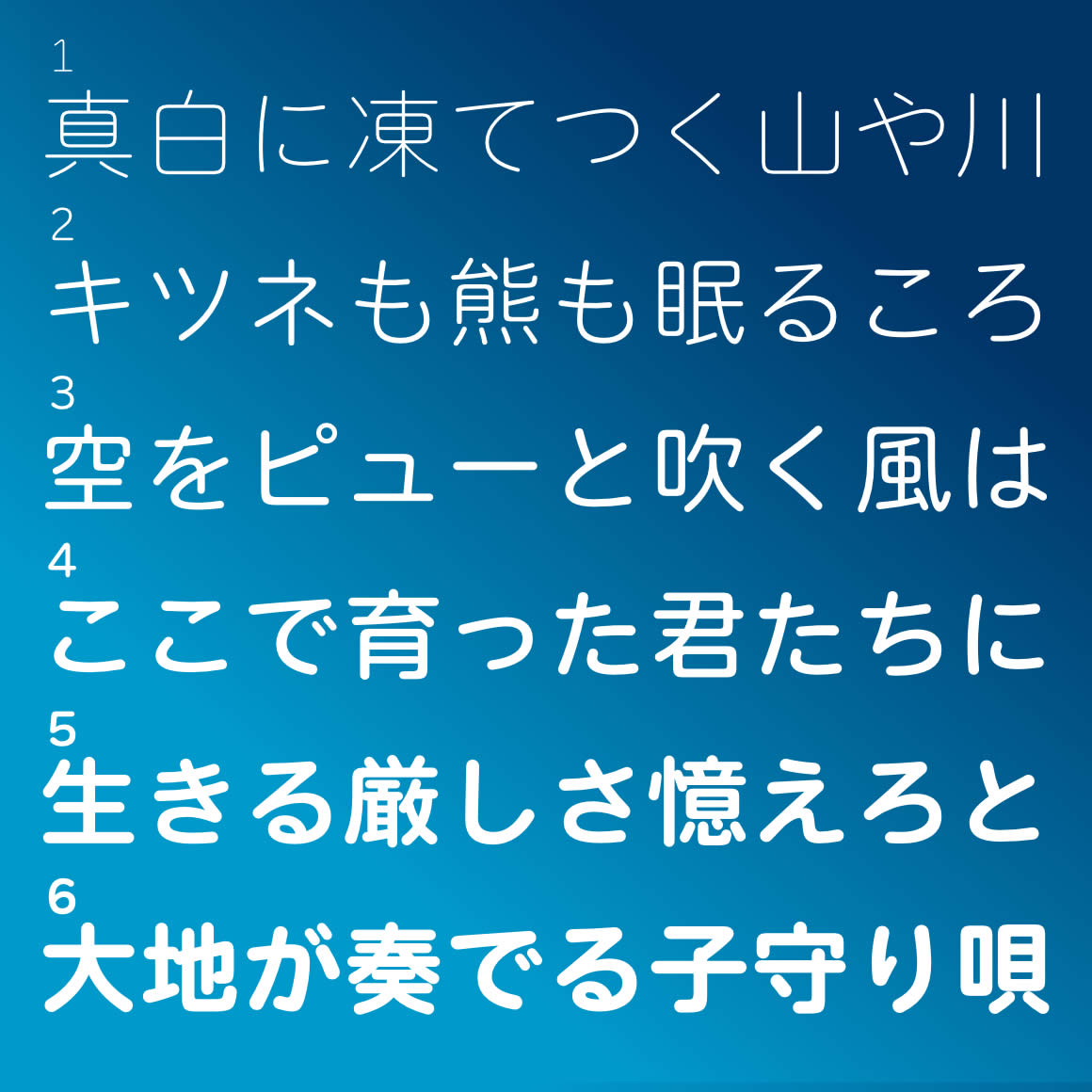
デザイン クセのないプレーンなイメージの丸ゴシック書体です。
太さが6種類あるので、使用環境や目的に合った最適なフォントが選べます。
等幅バージョンは、英大文字のアイ「I」と英小文字のエル「l」数字のいち「1」や、英大文字のオー「O」と数字のゼロ「0」が、はっきり区別がされているので、URL表記やプログラム編集などにぴったりです。
連想されるイメージ
寄せられたコメントから抜粋
美しい・柔らかい・読みやすい・プレーン・シンプル・やさしい・温かい・誠意を感じる・癖がない・標準的・バランスが良い・気持ち良い・ナチュラル・明るい・すっきりしている・落ち着きを感じる・安定している